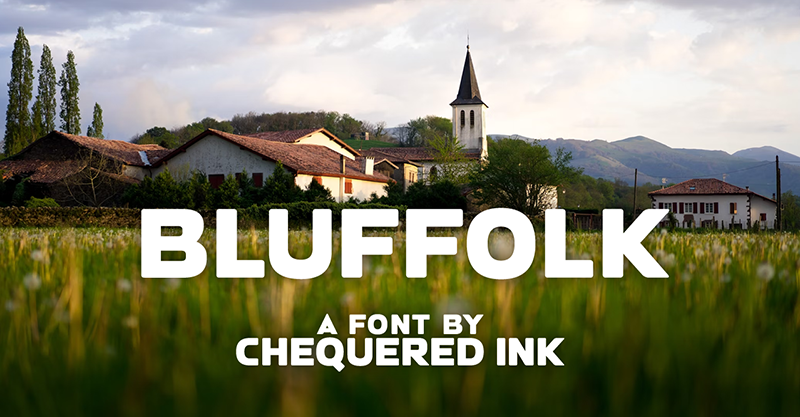
Font 1FTV Bluffolk là một kiểu chữ sans-serif được thiết kế bởi Chequered Ink và thuộc bộ font chữ 1 FTV. Phông chữ này, được biết đến với thiết kế hiện đại, sạch sẽ và tính linh hoạt, khiến nó trở nên lý tưởng cho nhiều mục đích sử dụng khác nhau như xây dựng thương hiệu, áp phích và nội dung kỹ thuật số. Font 1FTV Bluffolk mang đến tính thẩm mỹ đơn giản nhưng táo bạo, đảm bảo khả năng đọc và phong cách, đó là lý do tại sao nó phổ biến trong cả thiết kế kỹ thuật số và in ấn.